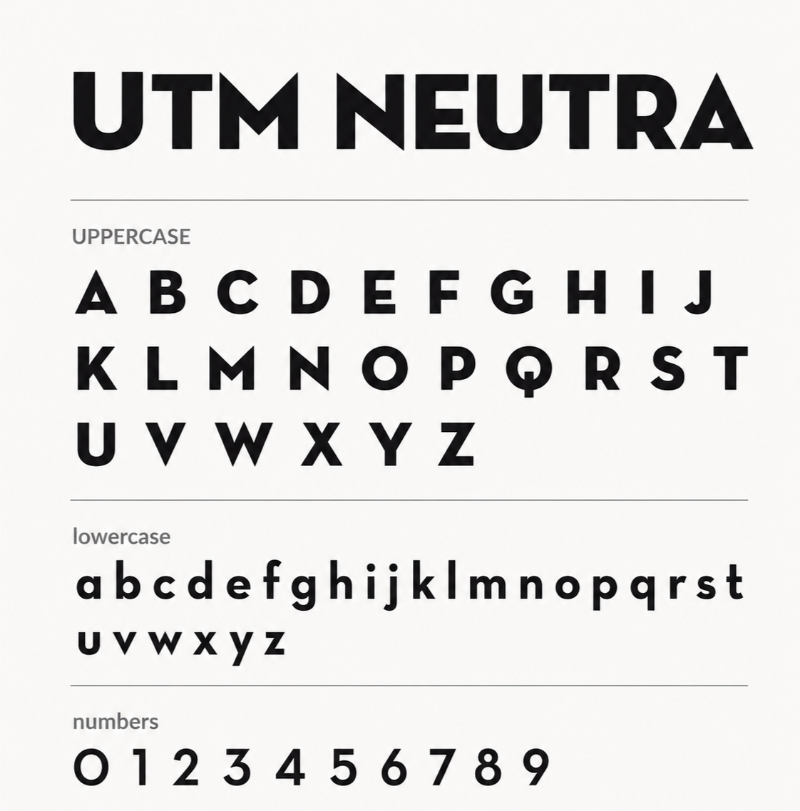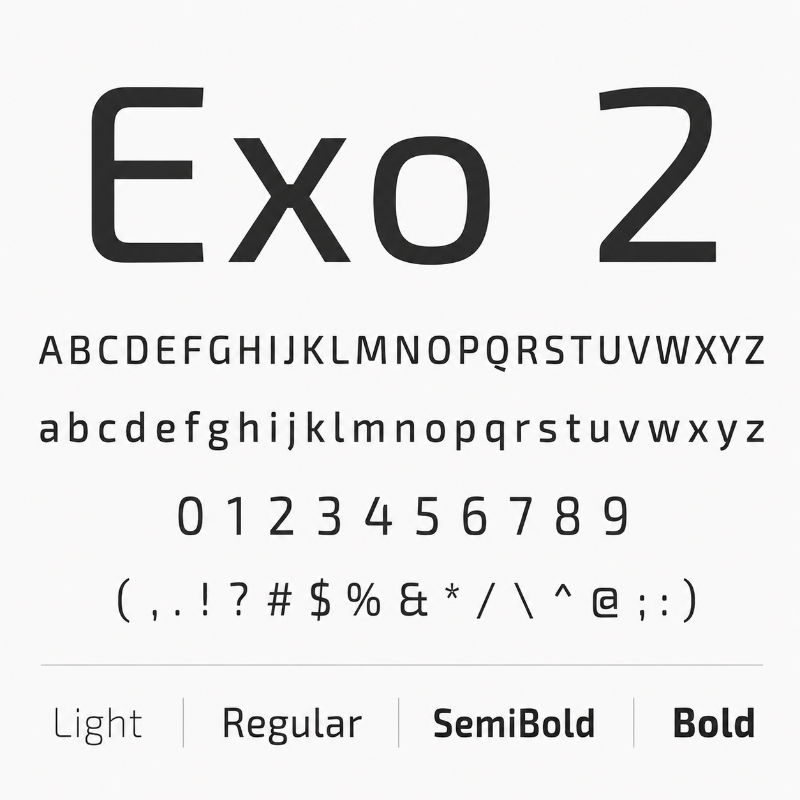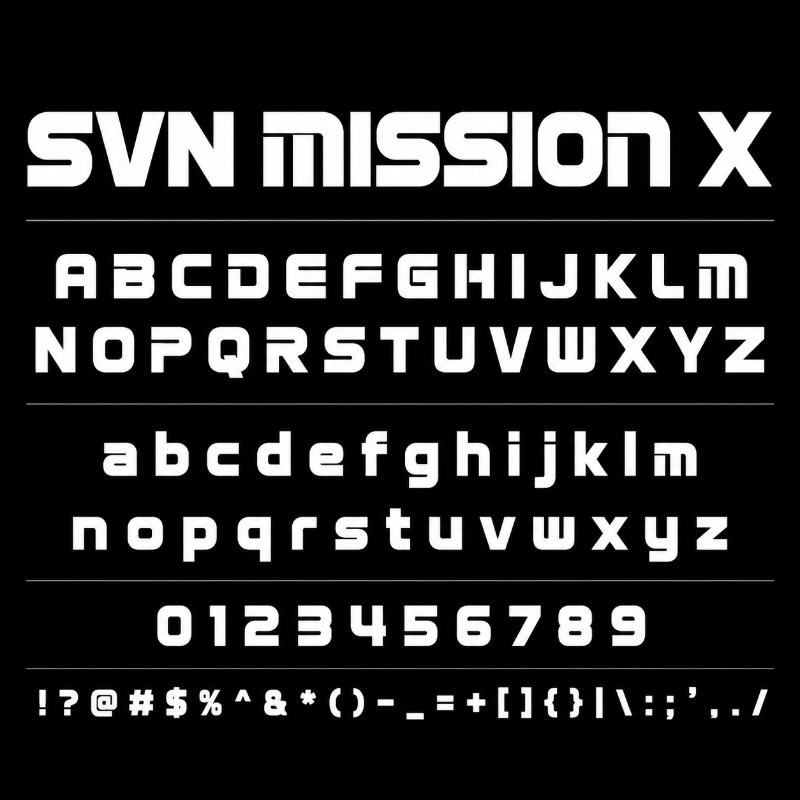
Nếu là một designer, chắc chắn bạn từng gặp tình huống khá khó chịu: tìm được một font chữ mang đậm tinh thần công nghệ, hiện đại và rất hợp concept, nhưng khi nhập tiếng Việt lại lỗi dấu. Kết quả là thiết kế vốn chỉn chu bỗng mất đi sự chuyên nghiệp và khó sử dụng trong thực tế.
Một font chữ công nghệ đúng nghĩa thường có đường nét gọn, sắc, thiên về hình khối rõ ràng. Chúng có thể thuộc nhóm sans-serif hiện đại hoặc monospace mang cảm giác lập trình, kỹ thuật. Khi sử dụng đúng cách, kiểu font này giúp thiết kế trở nên mạnh mẽ, tối giản, đột phá và đôi khi gợi liên tưởng đến thế giới tương lai, trí tuệ nhân tạo hoặc phong cách sci-fi.
Trong bài viết này, In Đại Minh sẽ chia sẻ đến các bạn 15+ font công nghệ Việt hóa miễn phí mới nhất 2026, cùng hướng dẫn ứng dụng thực tế. Từ thiết kế UI/UX, nhận diện thương hiệu, poster công nghệ cho đến giao diện game, mỗi gợi ý đều giúp bạn chọn font đúng ngữ cảnh và phối hợp hiệu quả hơn.
Tiêu chí quan trọng khi lựa chọn font chữ công nghệ
Một designer chuyên nghiệp sẽ không tải font một cách tràn lan, mà luôn có tiêu chí chọn lọc rõ ràng. Với font chữ công nghệ, bạn nên ưu tiên 3 yếu tố cốt lõi sau:
- Tính dễ đọc trên nền tảng số: Khi thiết kế giao diện website, ứng dụng hoặc dashboard, font chữ cần hiển thị sắc nét ở nhiều kích thước khác nhau. Đặc biệt, ở các cỡ chữ nhỏ như 12px hoặc 14px, ký tự vẫn phải rõ ràng, không bị dính nét hay gây khó đọc cho người dùng.
- Phù hợp với cá tính thương hiệu: Mỗi font chữ đều truyền tải một cảm giác riêng. Những font có đường nét vuông vức, góc cạnh thường phù hợp với lĩnh vực gaming, công nghệ phần cứng hoặc sản phẩm mang tính mạnh mẽ. Trong khi đó, các font có nét bo tròn mềm mại lại thích hợp với thương hiệu SaaS, AI, startup hoặc các dự án cần tạo cảm giác hiện đại, thân thiện và dễ tiếp cận.
- Hỗ trợ tốt tiếng Việt: Đây là tiêu chí không thể bỏ qua khi dùng font cho thiết kế tại thị trường Việt Nam. Font cần hỗ trợ đầy đủ Unicode tiếng Việt để các dấu như dấu hỏi, dấu ngã, dấu nặng, dấu sắc, dấu huyền hiển thị chính xác. Nếu font không tương thích, chữ có thể bị lỗi dấu hoặc tự động chuyển sang font mặc định, làm thiết kế mất đi sự đồng bộ và chuyên nghiệp.
Khám phá 15+ font chữ công nghệ Việt hóa ấn tượng
Để giúp bạn dễ dàng chọn được font chữ phù hợp với từng phong cách thiết kế, In Đại Minh đã tổng hợp danh sách 15+ font chữ công nghệ Việt hóa đẹp, hiện đại và dễ ứng dụng.
DVN Hexabot
Đây là font chữ mang đậm tinh thần robot và công nghệ cao. Các đường cắt xẻ mạnh, góc cạnh rõ ràng tạo cảm giác như những chi tiết cơ khí được lắp ghép với nhau. Font này rất phù hợp cho poster game, banner AI, thiết kế chủ đề robot, cyberpunk hoặc các dự án cần tạo ấn tượng mạnh ngay từ cái nhìn đầu tiên.
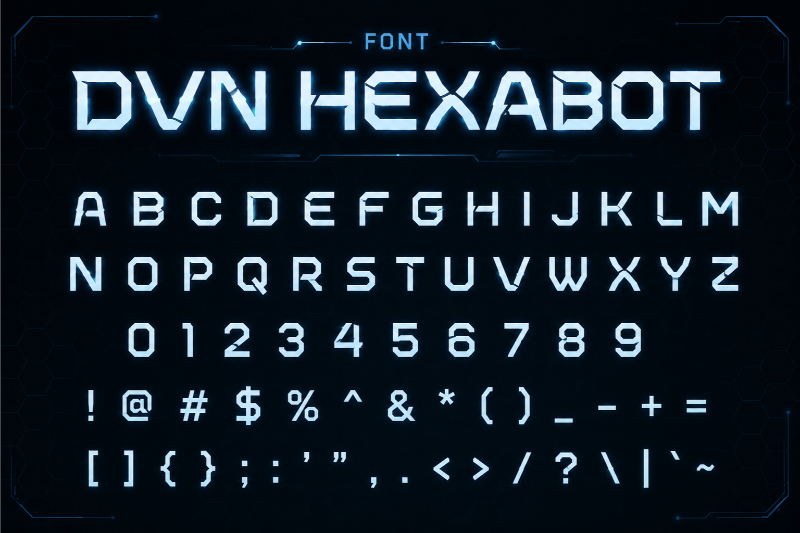
SVN Kelso
SVN Kelso gây ấn tượng bởi nét chữ dày, chắc và có độ vững chãi cao. Những đường nét gấp khúc tạo cảm giác hiện đại, cứng cáp và mang hơi hướng tương lai. Đây là lựa chọn đáng cân nhắc cho tiêu đề lớn, logo công nghệ, banner sự kiện eSports hoặc các thiết kế cần thể hiện sự mạnh mẽ, chuyên nghiệp.
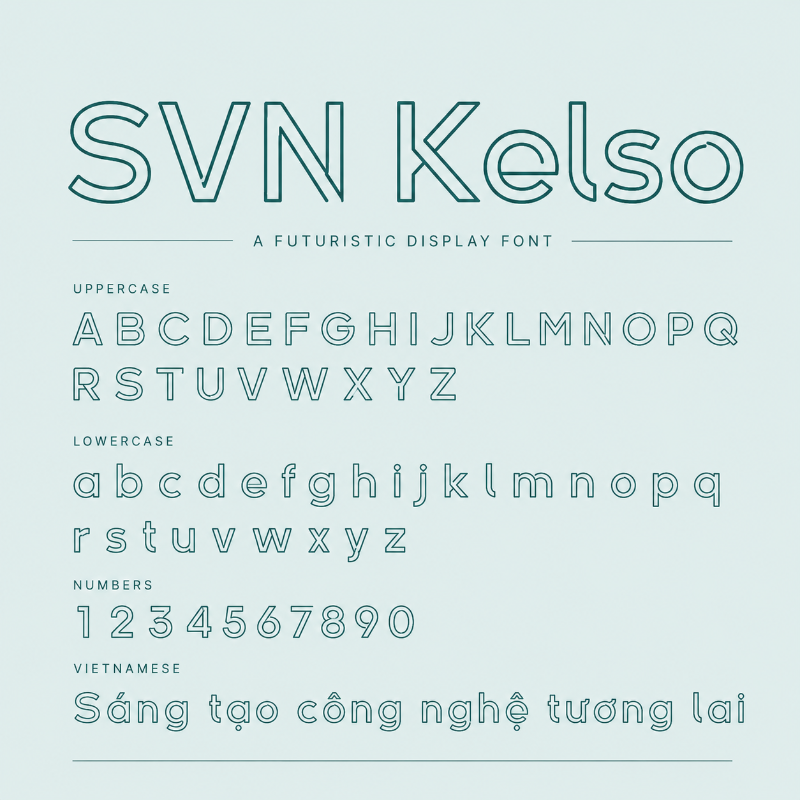
Aero Club Como
Aero Club Como là font chữ có dáng rộng, thuộc nhóm extended, giúp phần chữ trở nên bề thế và có chiều sâu thị giác. Kiểu chữ này mang lại cảm giác rộng lớn, hiện đại và gợi liên tưởng đến không gian vũ trụ. Font rất hợp với các thiết kế về hàng không, thiên văn, công nghệ tương lai, poster phim sci-fi hoặc các dự án cần tạo cảm giác hoành tráng.
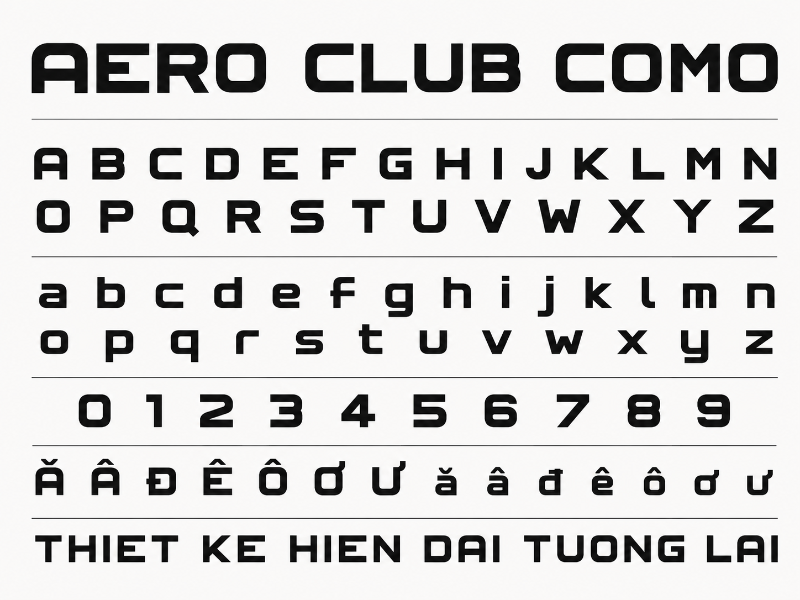
Orbitron Việt hóa
Orbitron là font chữ hình học không chân, được thiết kế chuyên cho các nội dung hiển thị mang phong cách tương lai. Các đường nét cân đối, sắc sảo và dễ nhận diện giúp font này xuất hiện nhiều trong thiết kế sci-fi, giao diện game, UI công nghệ, tiêu đề video và poster kỹ thuật số. Với bản Việt hóa, Orbitron trở nên tiện dụng hơn cho các dự án tiếng Việt mà vẫn giữ được tinh thần hiện đại, lạnh và đậm chất công nghệ.
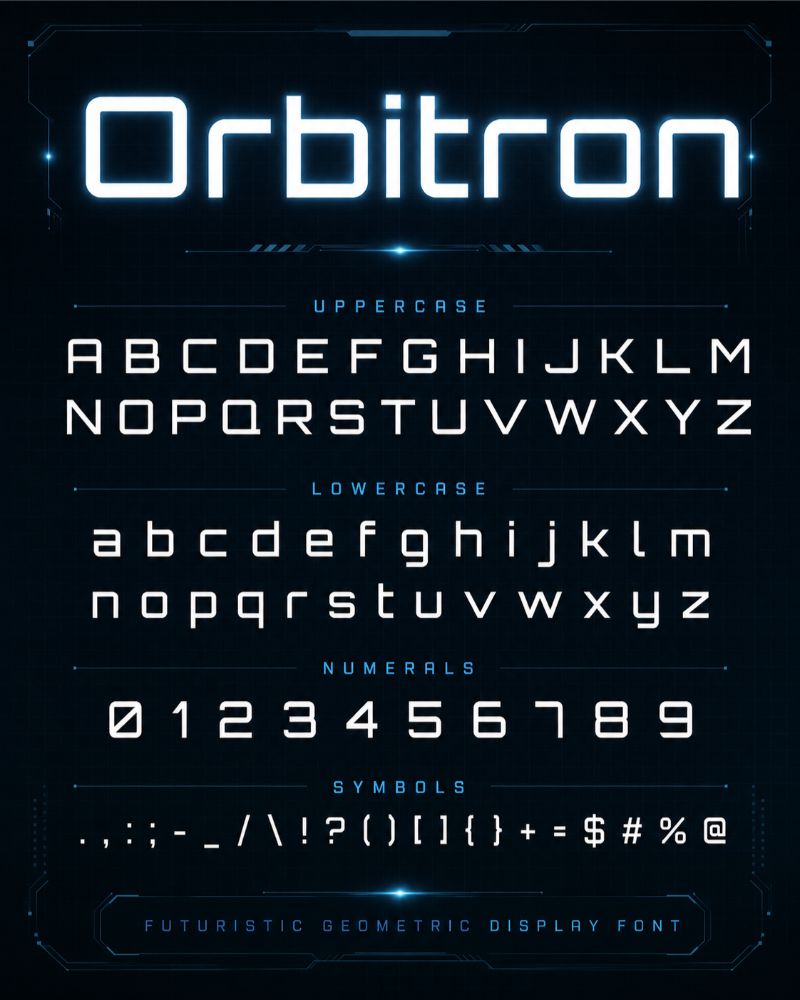
Space Mono
Space Mono mang phong cách monospace quen thuộc của thế giới lập trình, nhưng được xử lý mềm mại và dễ nhìn hơn. Font này tạo cảm giác kỹ thuật, gọn gàng và hiện đại, rất phù hợp với các startup công nghệ, cộng đồng developer, giao diện coding, landing page sản phẩm số hoặc các thiết kế cần gợi liên tưởng đến mã nguồn.
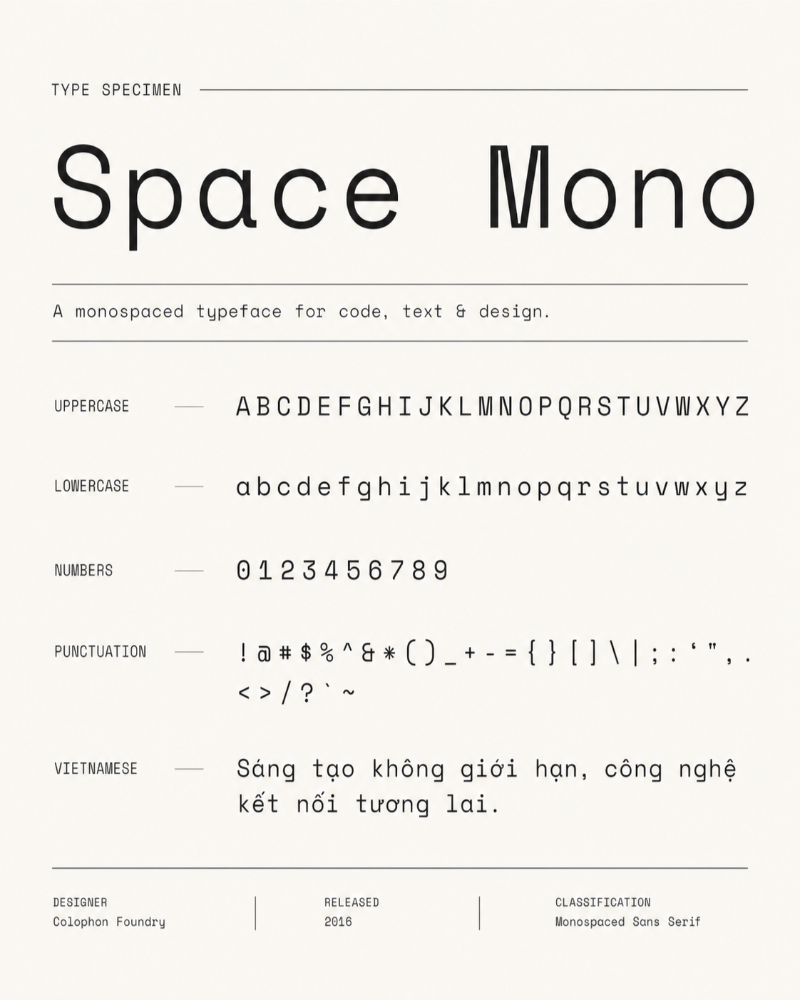
Courier Prime
Courier Prime là phiên bản được tinh chỉnh chỉn chu hơn từ kiểu chữ máy đánh chữ cổ điển. Font vẫn giữ được tinh thần retro, nghiêm túc và rõ ràng, nhưng dễ đọc hơn trên màn hình hiện đại. Đây là lựa chọn phù hợp cho code snippet, blockquote, tài liệu kỹ thuật, bài viết công nghệ hoặc các phần nội dung cần tạo cảm giác chuyên môn và đáng tin cậy.
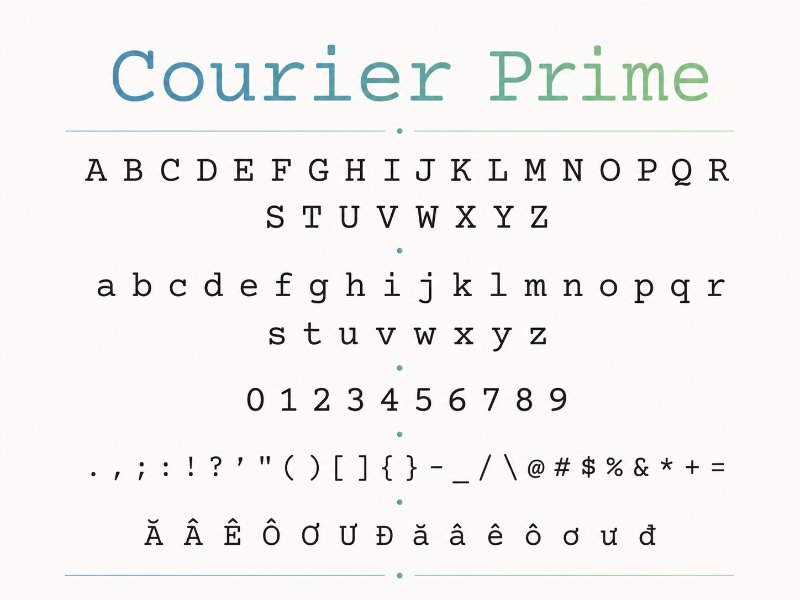
Gilroy Việt hóa chuẩn
Gilroy là dòng sans-serif hình học nổi bật với đường nét sạch, cân đối và hiện đại. Font này gần như là lựa chọn “quốc dân” trong thiết kế giao diện web, app, logo startup và nhận diện thương hiệu cho các công ty phần mềm. Bản Việt hóa chuẩn giúp Gilroy hiển thị tiếng Việt đẹp, đều dấu và chuyên nghiệp hơn trong các dự án thực tế.